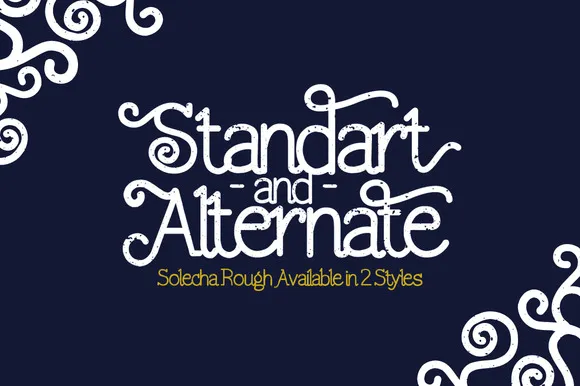
Solecha Rough Typeface – Download Grátis
Solecha Rough é uma tipografia monocorde que traz uma personalidade única. Este estilo moderno e único faz dele perfeito para projetos envolventes, desde embalagens de produtos até trabalhos editoriais e design de painéis. Suas linhas sólidas e definidas são muito legíveis, o que a torna ideal para criar um impacto forte e memorável em qualquer tipo de projeto visual. Solecha Rough também tem uma característica marcante: ele exala personalidade. Isso o torna perfeito não apenas para branding, mas também para eventos importantes como convites ou cartões. A elegância e a versatilidade desta fonte fazem dela uma escolha popular em diversas áreas do design gráfico.